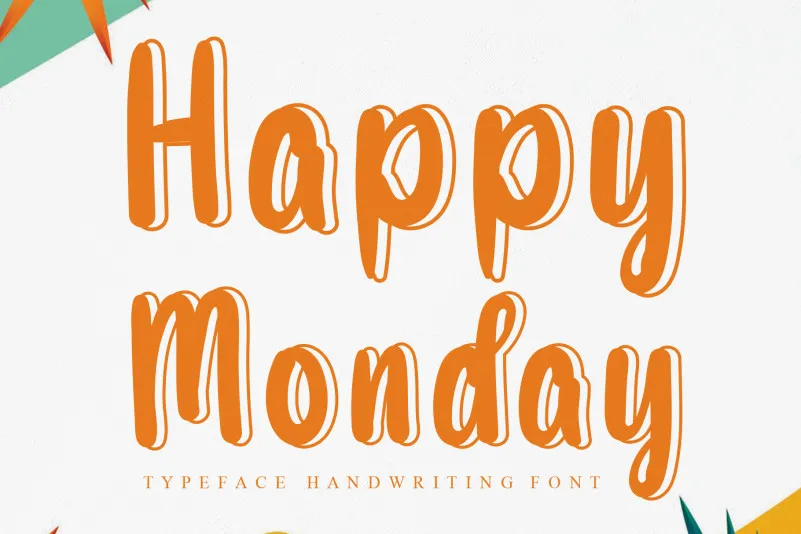
Happy Monday Display Font – Download Grátis
A Happy Monday Display Font é uma fonte de tipo exibição que traz letras marcantes e desenhadas com grande determinação e espessura. Com essa fonte, suas ideias criativas ganham um brilho especial, destacando-se na sua composição visual. É perfeita para aqueles momentos especiais do final de semana que precisam ser lembrados eternamente – seja em cartazes, banners ou outros materiais publicitários. Seja você o artista da semana, deixe sua marca com a Happy Monday Display Font.